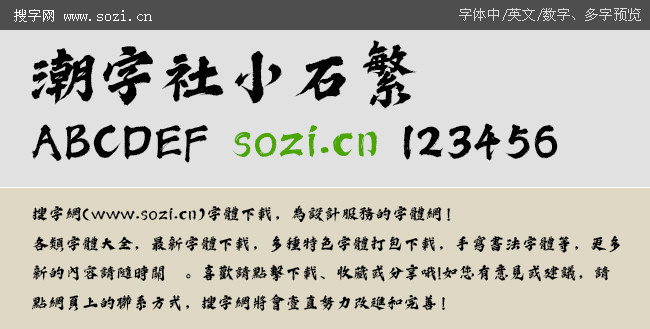
潮字社小石繁 最終版
搜字網(wǎng)提供一款潮字社小石繁 最終版中文字體下載,潮字社小石體遒美健秀,筆畫(huà)清晰明了,字型工整,具有極強(qiáng)的閱讀性,是一款為數(shù)不多的既適合標(biāo)題又適合正文的手寫(xiě)毛筆字庫(kù)。(此款為個(gè)人非商用版,如需商用請(qǐng)聯(lián)系銳字工房購(gòu)買(mǎi))
- 風(fēng)格類(lèi)別: 手寫(xiě)書(shū)法體